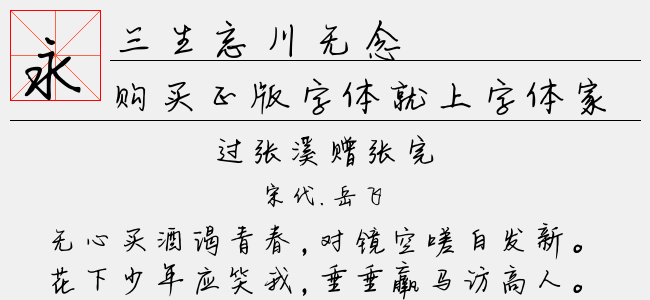
三生忘川无念
字体作者:三极字库
字体名称:三生忘川无念
字体家族:三极系列
书体类型:手写体/拼音
字体公司:三极字库
三生忘川无念
三生忘川无念这款字字体手写感强,编排时建议使得文字彼此间有位置偏差,更能挥发出字体本身的洒脱随性。适用于文艺类的书刊、品牌广告和产品包装设计,以及社交网络的个性化用字。